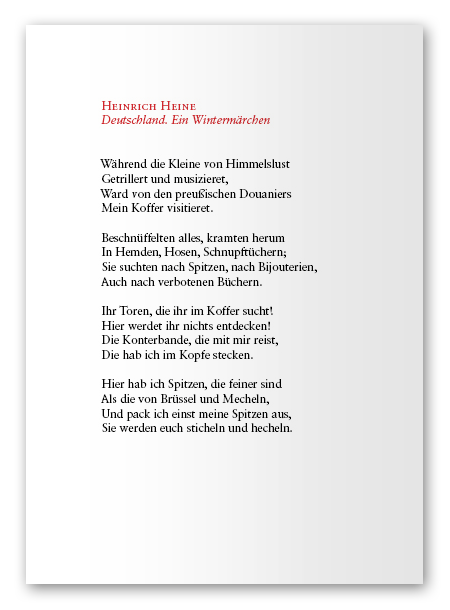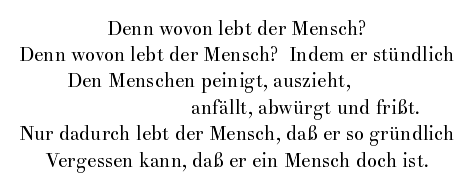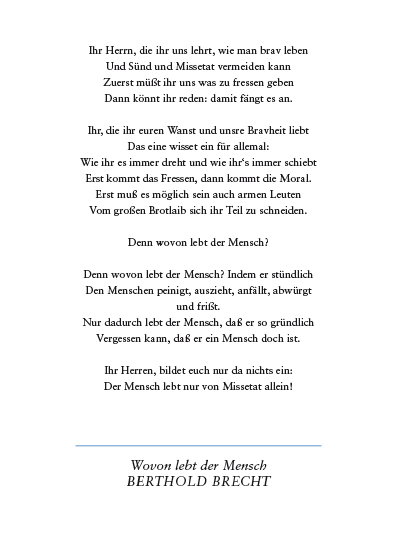
Das sieht man oft in den kleinen gelben Heftchen bei Dramen ... aber auch nur bei linksbündigem Satz :!:
Ich hatte aber tatsächlich schon überlegt den Überhang aus der Mitte rauszuziehen. Ob das geht? Ich weiß es nicht, hab’ mich nicht getraut es auszuprobieren :roll:
Eigentlich ist es der korrekte Weg, solche Überhänge rechtsbündig zu setzen. Ich hatte mir nur nicht gewagt, darauf hinzuweisen, weil ja Centrierung beschlossen scheint und ich mir das auch nur bei linksbündigem Satz vorstellen kann.
Aber lieber Kollege Scnitzel, ich muss auch mal sagen, dass Du es Dir selbst kompliziert machst (muss A6, muss zentriert, muss Sabon ...) und am Ende vermutlich keine perfekte Lösung dabei rauskommen wird ... Denk dran, Form follows function ...! ;-)
Stimmt. Gibt es denn alternativ ein neutrales Bindezeichen (also keine Ellipse), mit dem man am Ende der ersten Zeile andeuten könnte, dass die Gedichtzeile in der zweiten Zeile fortgesetzt wird?
Alles nicht ursprünglich dafür gedacht, aber hier evtl. brauchbar:
Zeilenende:
Zeilenanfang:
Ich hatte aber tatsächlich schon überlegt den Überhang aus der Mitte rauszuziehen. Ob das geht? Ich weiß es nicht, hab’ mich nicht getraut es auszuprobieren :roll:
Magst du deine Versuche nicht mal zeigen?
Aber lieber Kollege Scnitzel, ich muss auch mal sagen, dass Du es Dir selbst kompliziert machst (muss A6, muss zentriert, muss Sabon ...) und am Ende vermutlich keine perfekte Lösung dabei rauskommen wird ... Denk dran, Form follows function ...! ;-)
Wie gesagt, es gibt nur wenige Ausreißer, sonst gefällt es mir ganz gut.
Hier z. B. ›und frisst.‹, das gehört in die Zeile darüber. Der komplette Satzspiegel wandert evtl. noch weiter nach unten. Ich brauche aber noch eine Pagina o. ä., und ich bin mir noch nicht sicher, ob die oben oder unten hinkommt. Das ist hier aber auch nicht die Frage :-)
Dass diese Gestaltung nicht so richtig zu dem Herrn Brecht passen mag, ist mir auch klar. Aber ich sag mal so: Er fällt thematisch und formal auch sehr aus der Reihe. Hier sind nämlich auch die längsten Zeilen.
Dieses Projekt ist etwas sehr persönliches, aber die Frage schien mir allgemein sehr interessant. Es kann ja auch sein, dass man bei anderen Projekten mit Gedichten an solche Grenzen kommt.
Versuche doch mal folgendes: Setze die beiden Zeilen, die zu einem Vers gehören, so, daß sie sich überlappen, und mittele die beiden Zeilen dann als Ganzes.
Wenn ich ehrlich bin, finde ich die Mittelachse für ein Gedicht ziemlich verwirrend. Ich weiß, das hilft dir jetzt auch nicht viel weiter. Aber warum muss es unbedingt zentriert sein?
@ Joshua K.: Genau, gute Idee, beide Zeilen mitteln. Ich dachte bei dem Vorschlag oben nur an die untere Zeile ... Danke, ich werd’ es mal ausprobieren :-P
@Isa: Gerade bei Gedichten finde ich zentrierten Satz angebracht, da so jede Zeile mehr für sich steht und ihre eigene Wichtigkeit bekommt. Das kommt eher dem nahe, wie ich auch (laut) lesen würde. Natürlich gibt es auch Gedichte, bei denen die entstehende Form im linksbündigen Satz entschieden dazugehört.
Ich habe gerade mal stichprobenartig die Lyrikabteilung meiner Hausbibliothek durchgesehen und so auf Anhieb nur linksbündige Gedichte gefunden :-o
Ich werde es noch mal überdenken und ich bin ja nicht so borniert, dass ich einmal gemachte Entscheidungen nicht revidieren könnte ... aber ehrlich gesagt finde ich zentrierten Satz schlüssiger, denn warum sollte ich die linke Kante derartig betonen :-?
Ich habe gerade mal stichprobenartig die Lyrikabteilung meiner Hausbibliothek durchgesehen und so auf Anhieb nur linksbündige Gedichte gefunden :-o
Ich habe schon auch Gedichte gefunden, die zentriert sind. Aber dann sind es nur ganz kurze, die das Problem mit dem Umbruch nicht haben.
denn warum sollte ich die linke Kante derartig betonen :-?
Um das Problem zu vermeiden vor dem du gerade stehst? :-?
Ich habe schon auch Gedichte gefunden, die zentriert sind. Aber dann sind es nur ganz kurze, die das Problem mit dem Umbruch nicht haben.
Ich hab das schon bei Liedtexten im Internet gesehen ... Aber da kann man auch rein und raus zoomen ...
Um das Problem zu vermeiden vor dem du gerade stehst? :-?
+1 :) Form follows function bewahrheitet sich immer wieder ... ;)
Wie wär es denn, das A6-Format quer zu binden? Vielleicht kommt das besser ...? :-?
Ich hab das schon bei Liedtexten im Internet gesehen ... Aber da kann man auch rein und raus zoomen ...
+1 :) Form follows function bewahrheitet sich immer wieder ... ;)
Wie wär es denn, das A6-Format quer zu binden? Vielleicht kommt das besser ...? :-?
Beim Durchsehen meiner kleinen Gedichtsammlung fand ich immer wieder, dass die Gedichte nicht richtig zur Geltung kommen und die Weißräume rechts und links nie richtig harmonisch sind.
Bei näherer Betrachtung braucht der auch noch etwas mehr Luft und Durchschuss ... [/img]
Ja, ich hatte schon überlegt, ob ich das gleich dazu schreiben sollte, aber ...
Sind die Gedichte alle so kurz, dass sie auf eine Seite passen? Und wenn nein: was machst du dann mit Autor und Titel, wenn sie unten auf der Seite stehen sollen?